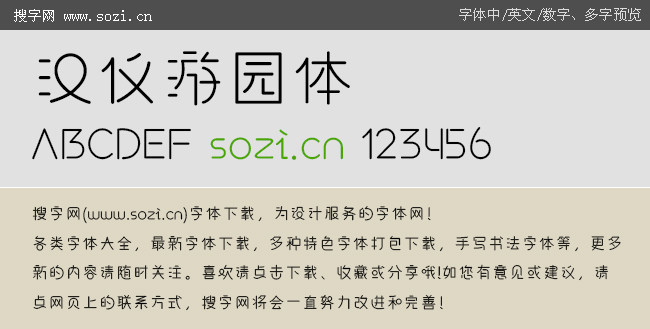
漢儀游園體
搜字網(wǎng)給大家提供一款漢儀游園體中文字體下載。漢儀游園體嘗試借鑒蘇州園林中的元素引入漢字的字體設(shè)計(jì)之中,希望由此能產(chǎn)生一種新的閱讀體驗(yàn),為了能夠突顯園林的美學(xué)特征,在字體筆畫的設(shè)計(jì)上,以園林中各元素的造型為借鑒,意象性的在字體中表現(xiàn)園林的形態(tài)。適合產(chǎn)品畫冊(cè)、產(chǎn)品包裝設(shè)計(jì)、海報(bào)設(shè)計(jì)、網(wǎng)頁(yè)標(biāo)題設(shè)計(jì)等應(yīng)用。(本字體為個(gè)人非商用版,如需要商用請(qǐng)聯(lián)系漢儀公司購(gòu)買版權(quán))